เผยภาพเสื้อแจ็กเก็ต WWDC 2015 สกรีนฟ้อนต์ San Francisco และโค้ด Swift
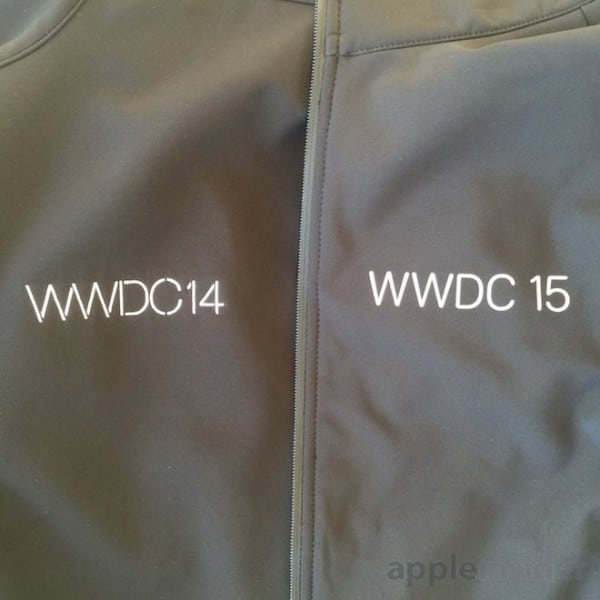
เผยภาพลายเสื้อของ WWDC 2015 ที่จะแจกผู้ร่วมงานทุกคน โดยครั้งนี้สกรีนฟ้อนต์ San Francisco แบบเดียวกับที่ใช้บน Apple Watch
สำหรับเสื้อ WWDC 2015 นี้ไม่มีโลโก้ Apple แต่อย่างใด มีเพียงลาย WWDC 15 อยู่ด้านหน้าและเลข 15 ตัวใหญ่อยู่ด้านหลังเป็นฟ้อนต์ San Francisco ส่วนที่แปะป้ายเสื้อเขียนเป็นโค้ดภาษา Swift
การใช้ฟ้อนต์ San Francisco บนเสื้อแจ็กเก็ต น่าจะเป็นการบอกอย่างเป็นนัยว่า Apple เตรียมจะใช้ฟ้อนต์ San Francisco กับ OS X และ iOS แล้วก็ได้ จากปัจจุบันที่ฟ้อนต์นี้ใช้อยู่บน Apple Watch เท่านั้น โดยฟ้อนต์นี้จะเป็นฟ้อนต์ที่ Apple ออกแบบเองเพื่อการมองเห็นบนจอเล็ก